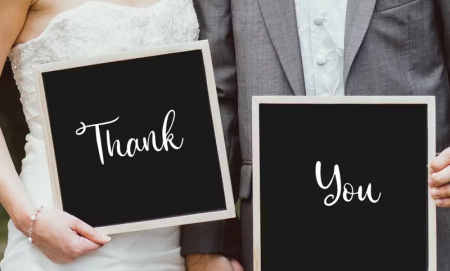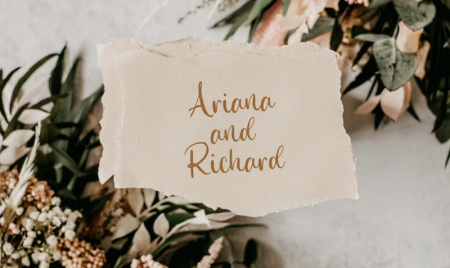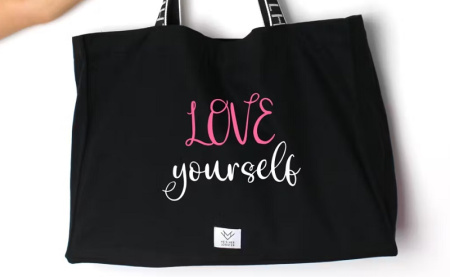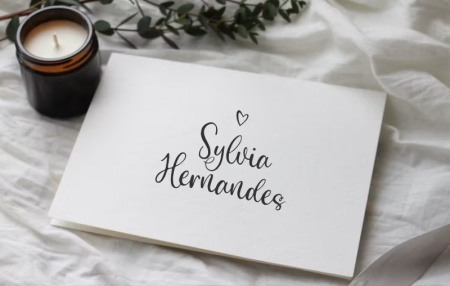
فونت انگلیسی رایگان Magical Spring
فونت انگلیسی رایگان Magical Spring. یک فونت اسکریپت دوست داشتنی است که برای کاردستی، برندسازی، دعوت نامه، لوازم التحریر، طرح های عروسی، پست های رسانه های اجتماعی، تبلیغات، بسته بندی محصول، طرح های محصول، برچسب، عکاسی، واترمارک، رویدادهای خاص یا هر چیز دیگری مناسب است. برای مشاهده تصاویر این فونت و دانلود رایگان آن از gfxdownload در ادامه مطلب با ما همراه باشید.
✅ نام فونت: Magical Spring
✅ حروف بزرگ و کوچک
✅ اعداد و نقطه گذاری
✅ PUA کدگذاری شده است
✅ پشتیبانی چند زبانه